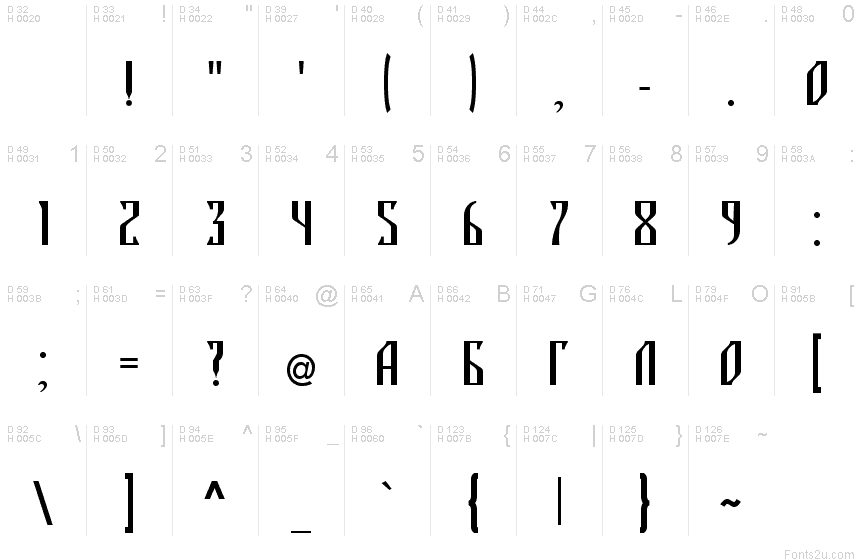
Blago autorstwa Nikoli Kovanovicia to darmowy, cyryliczny krój typu display, wyróżniający się wyrazistym, niemal liturgicznym, słowiańskim klimatem. Litery są wysokie i masywne, z ostrymi wewnętrznymi wycięciami i zdecydowanymi pionowymi łukami, co sprawia, że całość wygląda jak wykuta w kamieniu, a nie narysowana.
Krój ten doskonale sprawdzi się w tytułach plakatów, oprawach muzycznych, okładkach książek, identyfikacji wizualnej wydarzeń kulturalnych oraz krótkich nagłówkach redakcyjnych, w których ten surowy, ceremonialny ton wzmacnia przekaz. Jako darmowy font, idealnie nadaje się również do plansz tytułowych, monogramów i inicjałów – jego gęste sylwetki i ostre kąty przykuwają uwagę nawet w bardzo krótkich tekstach.